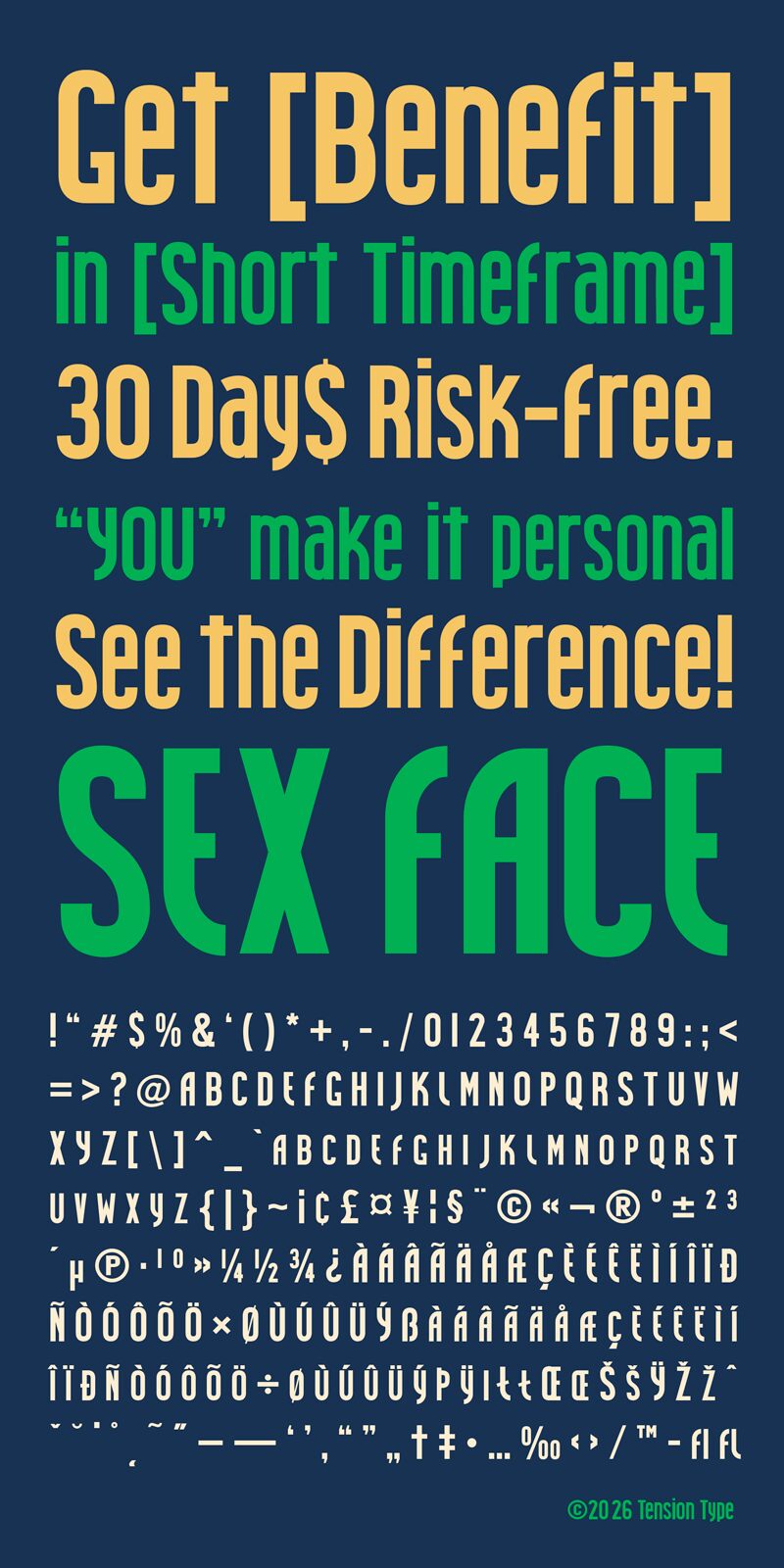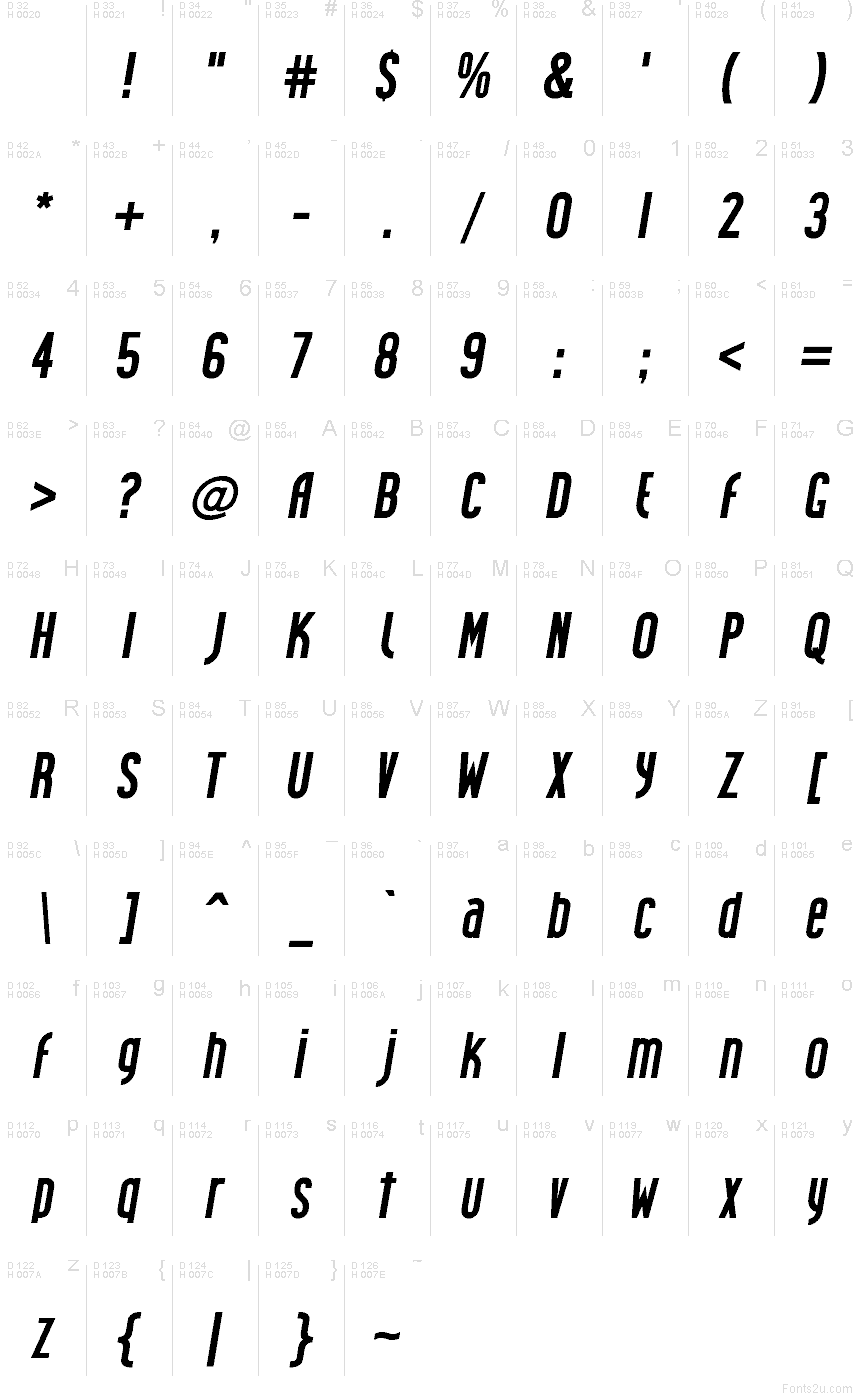
Sex Face Italic
Sex Face Italic es una tipografía display retro gratuita de estilo sans serif, redondeada, inclinada y con formas estrechas que aportan una sensación de movimiento hacia adelante. Sus curvas son suaves, sus perfiles sencillos y el ángulo de la cursiva le otorga un ritmo condensado, muy al estilo de los carteles clásicos.
Sex Face Italic funciona de maravilla en portadas de álbumes, flyers de eventos, logotipos vintage, packaging y nombres de marca cortos, ya que su diseño transmite un potente espíritu de los años 70 sin adornos superfluos. Esta fuente gratuita también encaja a la perfección en cabeceras, carteles y gráficos para redes sociales cuando buscas un estilo display compacto con un toque retro cálido.
Mi segundo diseño de una tipografía sans serif. Me encanta la tipografía condensada, así que eso es precisamente lo que hice. Ideal para titulares, pósteres, logos o cualquier aplicación de gran formato. No es la opción más adecuada para textos largos.
Tension Type
Michael Tension
My second design of a sans serif font. I like condensed type a lot, so that’s what I did. A big learning curve!